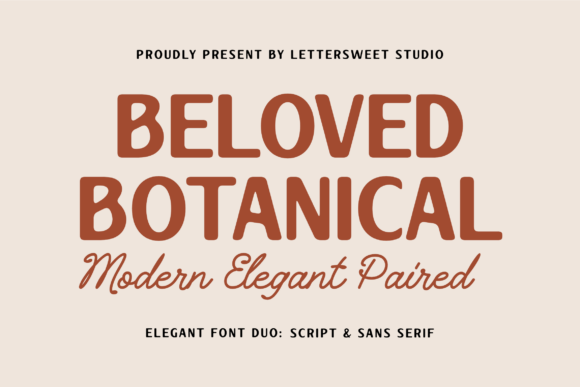
Beloved Botanical
Jika anda sedang mencari aset berkualiti tinggi seperti Beloved Botanical, pakej premium ini merupakan pilihan yang hebat untuk projek kreatif anda.
Sama ada anda mencipta produk POD (Print on Demand), jemputan perkahwinan atau grafik media sosial, Beloved Botanical amat bersesuaian.